Kerning to detal, który bardzo szybko zdradza, czy skład jest dopracowany. W praktyce odpowiedź na kerning co to sprowadza się do jednej rzeczy: precyzyjnego ustawienia odstępu między konkretnymi parami znaków, tak aby litery wyglądały naturalnie, a tekst był czytelny i estetyczny. W projektach do druku, albumach fotograficznych, zaproszeniach czy logo ten drobny parametr potrafi zmienić odbiór całej pracy.
Najważniejsze informacje w skrócie
- Kerning reguluje odstęp między konkretnymi parami znaków, a nie między wszystkimi literami naraz.
- Najbardziej widać go w nagłówkach, logotypach, okładkach i innych elementach z dużym stopniem pisma.
- Kerning nie jest tym samym co tracking ani leading, choć te pojęcia często się mylą.
- Źle ustawiony kerning psuje rytm słowa: tworzy dziury, zlepia litery albo daje wrażenie przypadkowości.
- W gotowych fontach wiele par jest ustawionych automatycznie, ale w projektach premium często potrzebna jest ręczna korekta.
- Najlepszy efekt daje sprawdzanie kerningu w realnym rozmiarze, na docelowym nośniku i w kontekście całego słowa.
Czym jest kerning i kiedy ma znaczenie
Kerning to korekta odstępów między dwoma sąsiadującymi znakami, która ma sprawić, że słowo będzie wyglądało optycznie równo. Nie chodzi tu o matematyczną symetrię, tylko o to, jak oko odbiera kształt litery i białą przestrzeń wokół niej. Dlatego para znaków AV zwykle wymaga innego ustawienia niż OO czy NN.
W gotowych krojach pisma projektant zapisuje domyślne odstępy, ale one nie zawsze pasują do każdego układu. Najczęściej problem widać w zestawieniach takich jak To, Ta, Wa, VA czy LT, gdzie jedna litera ma skos, a druga zostawia wizualną lukę. Właśnie dlatego kerning ma największe znaczenie w nagłówkach, logotypach, opakowaniach, podpisach pod zdjęciami i wszędzie tam, gdzie tekst ma nie tylko informować, ale też dobrze wyglądać.
W długim tekście roboczym wpływ kerningu bywa mniejszy, bo wzrok czyta całe linie, a nie pojedyncze pary znaków. Z kolei w dużych napisach nawet drobna nieszczelność natychmiast rzuca się w oczy. Z tego powodu ja zwykle traktuję kerning jako narzędzie precyzji, a nie ozdobę samą w sobie. Żeby z niego korzystać świadomie, trzeba jeszcze odróżnić go od dwóch innych pojęć, które w typografii myli się najczęściej.
Kerning, tracking i leading to nie to samo
Adobe i Monotype zwracają uwagę na to samo rozróżnienie: kerning dotyczy konkretnych par znaków, a nie równomiernego rozciągania całego tekstu. To ważne, bo wiele osób poprawiających skład zbyt szybko sięga po zły parametr i próbuje jednym ruchem naprawić problem, który wymaga punktowej korekty.
| Termin | Co reguluje | Jak działa w praktyce | Kiedy używam |
|---|---|---|---|
| Kerning | Odstęp między dwiema konkretnymi literami lub znakami | Koryguje pojedyncze, problematyczne pary | Logotypy, nagłówki, duże napisy, dekoracyjne składy |
| Tracking | Odstęp między wszystkimi znakami w wybranym fragmencie | Rozsuwa lub ściska cały wyraz, zdanie albo blok tekstu równomiernie | Wyrównywanie nastroju tekstu, wersaliki, teksty ekspozycyjne |
| Leading | Odstęp między wierszami | Kontroluje pionowy rytm bloku tekstu | Akapity, dłuższe publikacje, skład wielowierszowy |
W praktyce to właśnie tracking bywa nadużywany jako szybka poprawka, choć powinien służyć do czegoś innego. Jeśli cały wyraz wygląda zbyt ciasno, najpierw sprawdzam kerning par problemowych, a dopiero później myślę o ogólnym światle. Gdy tę kolejność się odwróci, efekt często robi się sztuczny. To prowadzi do kolejnego pytania: po czym poznać, że kerning jest naprawdę dobry, zanim projekt trafi do druku.
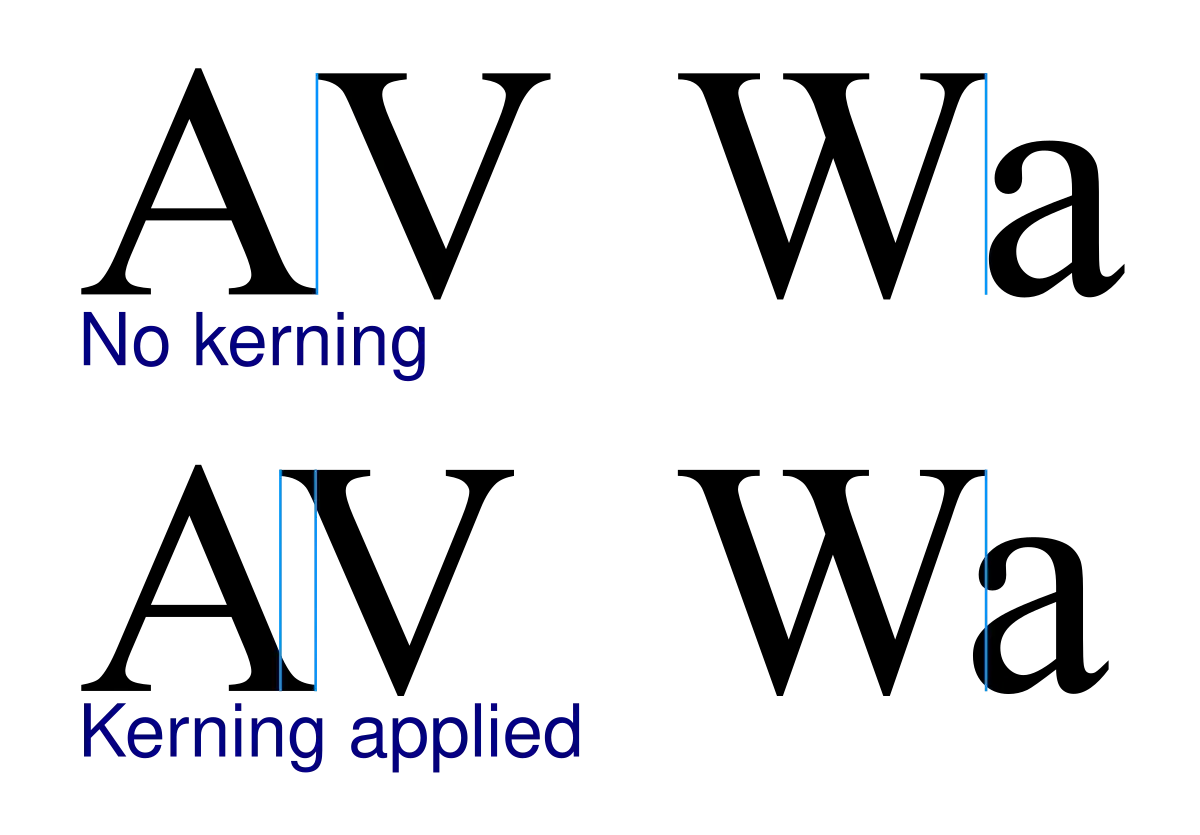
Jak rozpoznać dobry i zły kerning na pierwszy rzut oka
Dobry kerning nie krzyczy. Po prostu sprawia, że litery składają się w słowo, które ma równy rytm i nie ma w nim dziwnych „dziur” ani zatorów. Gdy patrzę na napis, szukam przede wszystkim tego, czy białe przestrzenie między znakami są optycznie podobne, nawet jeśli technicznie nie mają identycznej szerokości.
Najczęściej problematyczne pary
- AV, VA, WA - ukośne litery zostawiają zbyt dużo pustki, jeśli nie zostaną dociśnięte.
- To, Ta, Te - pozioma belka i zaokrąglenie często wymagają korekty.
- LT, LY, TY - połączenie pionowej litery z ukośną bywa wizualnie nierówne.
- Yo, Wa, We - szerokie formy tworzą nadmiar bieli po jednej stronie.
- rn, nn, cl - tu problemem bywa nie tylko odstęp, ale też złudzenie zlepienia kształtów.
Na co patrzę podczas oceny
Najprostszy test jest banalny: mrużę oczy albo patrzę na napis z większej odległości. Jeśli słowo zaczyna „falować” albo jedna para znaków od razu wybija się z rytmu, kerning wymaga korekty. W dobrze ustawionym napisie nie ma przypadkowych ciężarów po jednej stronie, a żadna para liter nie wygląda jakby była wciśnięta na siłę albo odklejona od reszty.
Ważny jest też kontekst. Ten sam zestaw liter może wyglądać dobrze w jednym kroju i źle w innym, bo różnią się kształtem znaków, kontrastem i proporcjami. Dlatego nie oceniam kerningu na pojedynczych literach oderwanych od słowa. Zawsze patrzę na całość. Kiedy już widać, że problem istnieje, warto wiedzieć, jak wygląda proces jego poprawiania w różnych środowiskach pracy.
- Nie poprawiaj wszystkiego naraz, tylko usuń te miejsca, które rzeczywiście psują rytm.
Kerning nie jest dodatkiem dla estetów, tylko jednym z narzędzi, które decydują o jakości składu. Gdy jest dobrze ustawiony, tekst wygląda pewniej, a odbiór projektu staje się spokojniejszy i bardziej profesjonalny. W projektach związanych z fotografią i drukiem ten efekt szczególnie się liczy, bo właśnie detal często przesądza o tym, czy całość wygląda jak dopracowana realizacja, czy jak szybki szkic bez kontroli nad typografią.